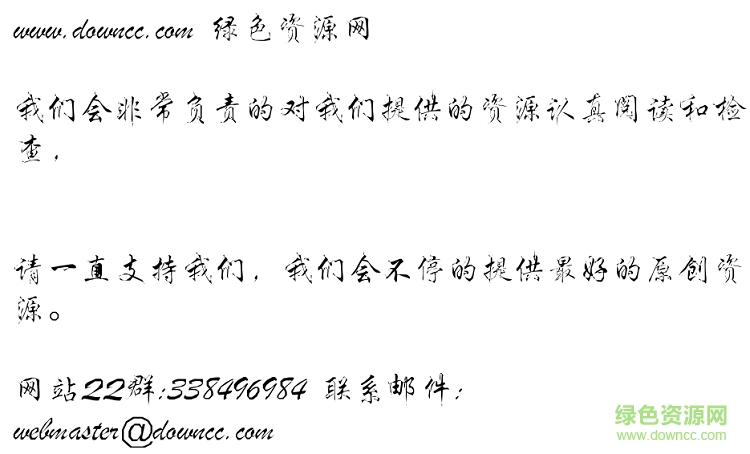
福順飄逸云煙字體
飄逸云煙字體是福順系列的一款藝術(shù)字體,字跡若隱若現(xiàn)如置云煙之中,有著霧氣縹緲的零離感,連筆的構(gòu)造讓字體更加飄逸灑脫,喜歡的朋友就來綠色資源網(wǎng)免費(fèi)下載吧!
福順飄逸云煙字體介紹
福順系列是產(chǎn)量比較高的藝術(shù)字體,打造不同尋常的特色書法,讓你的平面設(shè)計雨中不同,每一個字體都有不一樣的藝術(shù)魅力,讓使用的行業(yè)更加多變,無論是廣告創(chuàng)意還是印刷排版都很試用!
飄逸云煙